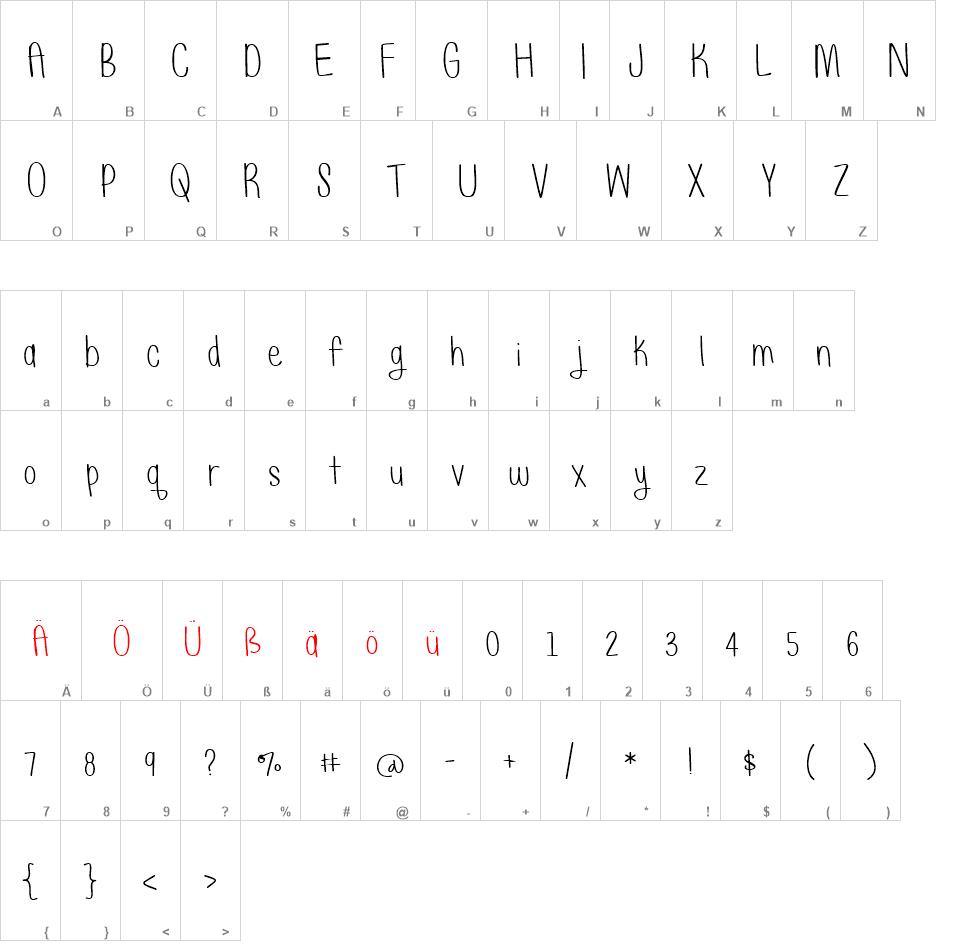
Just Alice
Just Alice font
Just Alice
Just Alice ist eine natürliche, unkomplizierte Handschrift mit Alternativen und Ligaturen. Organisch und dennoch gut lesbar ist Just Alice ideal, um Ihren Notizen, Überschriften, Zeilenumbrüchen oder sogar Text Persönlichkeit zu verleihen.